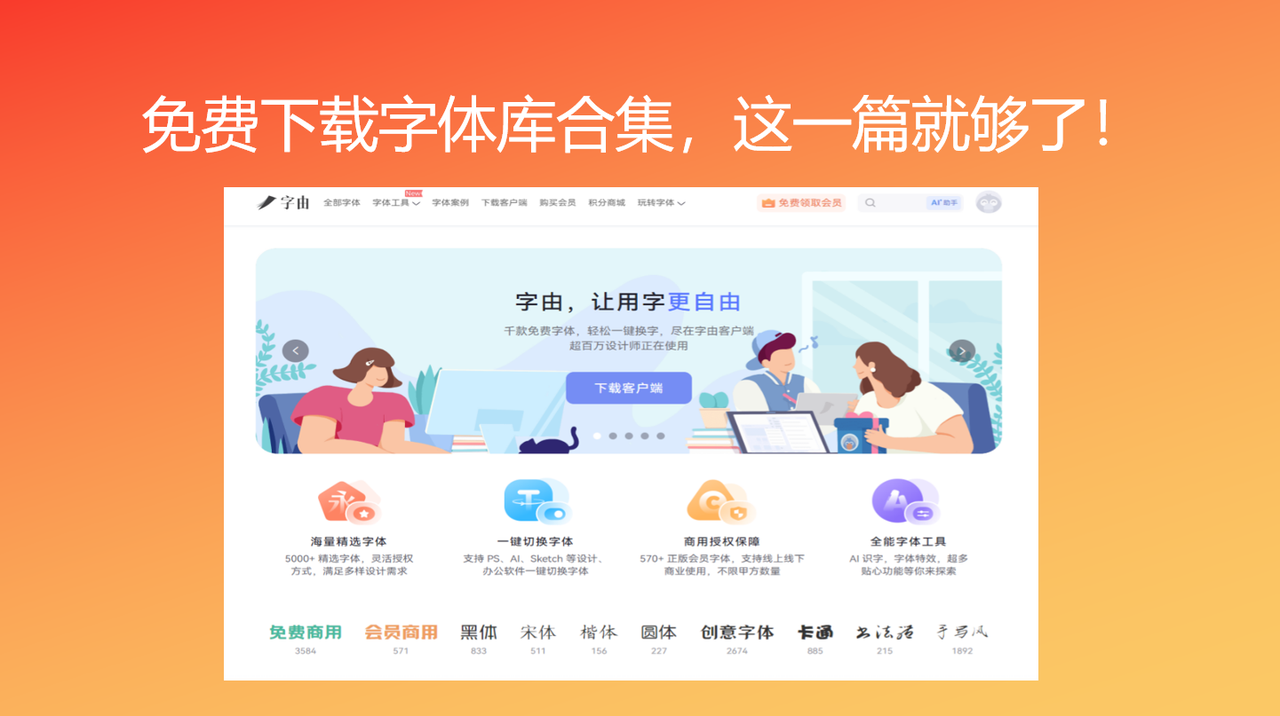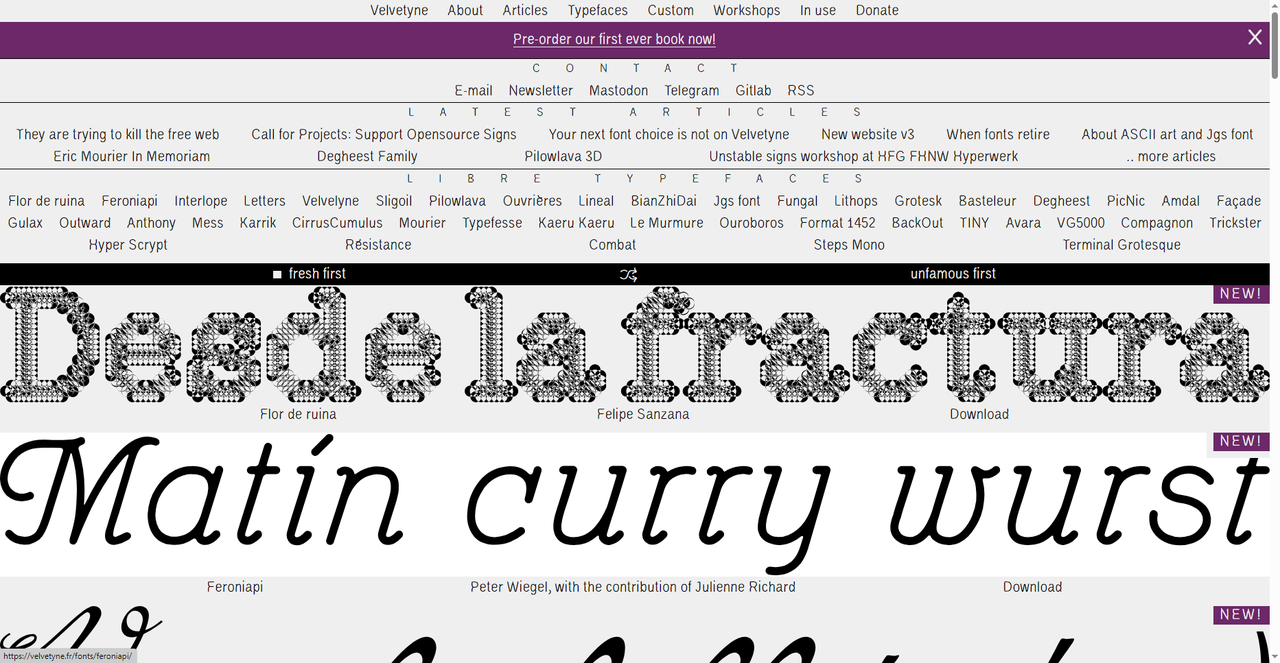
免费下载字体库合集,这一篇就够了!
相信各位和及时的浏览器收藏夹里肯定有专门分类收藏字体网站的收藏栏,看到别人推荐就点进去收藏,时间一长肯定有不少积累了。但是真正做项目的时候反而开始头疼要从这些花里胡哨的网站挑选哪个,有的网站已经好久都没有更新了,有的是分类太乱翻不到想要的,有的还要下载客户端,或者是注册邮箱,最后往往还是去搜“免费下载字体库”,从头开始找。今天我就为各位设计师推荐 5 个真正好用、经常能拿来使用的字体库,想要免费下载字体库,看这一篇就够了!
我经常用的免费下载字体库是字由。它里面涵盖了 5000 款字体,直接打包成一个超级字体库,它不需要你一个一个下载、安装客户端等等麻烦的步骤,你只需要点进网页版然后通过手机号注册即可。下面我会分享详细的使用教程。
- 按类型:黑体、宋体、书法体、手写体、Sans Serif、Serif 等
- 按热度:每款字体右下角有使用次数,优先选热度高的,比如“优设好身体”使用量达499万次
我可以推荐几款我自己经常用到的字体:
- 优设好身体(499万次使用):优设团队出品,字形方正饱满,适合正文排版和简洁标题。做画册、公众号配文很好用。
- 字由源黑95(6.5万+次使用):一款厚实稳重的黑体,字重足够“黑”,适合做标题、海报主视觉,视觉冲击力强。
- 点字婴宝(12万次使用):可爱风格的手写字体,圆润稚趣,适合母婴、儿童、萌系风格的设计。
- 字由玉润体(6.7万+次使用):圆润柔和的字体,笔画温润如玉,适合女性向、美妆、护肤等柔和风格的设计。
2、Velvetyne
Velvetyne 是一个来自法国的开源字体合作社,把自己定位为“自由字体合作社”。它的免费下载字体库里全是开源字体,可以免费商用,甚至允许修改和再分发。这样自由度如此之高的免费下载字体库合集网站基本上可以满足你的一站式需求,尤其是那些需要自主设计字体的字体设计师们。从图中不难看出首页有丰富的字体类型,Flor de ruina、Feroniapi、Interlope、Gulag、Outward、Anthony、Mess、Karrik、Letters……风格非常多元,每一款都有设计师的详细信息,可以点进去查看详情。
3、Collletttivo
这个网站是一个开源字体代工厂,也是设计师们协作创办的网络,这个网站主打宣传“通过相互交流和协作促进字体设计实践”,目前这个网站有16款开源字体,展示了7款:Borges、Ronzino、Aujournuit、Abasans、Coconut、Apple Grotesk、Sinistre。这款免费下载字体库合集中的字体适合追求简洁、现代感的设计师,尤其是品牌设计、网页设计项目。下载方式也很直接。
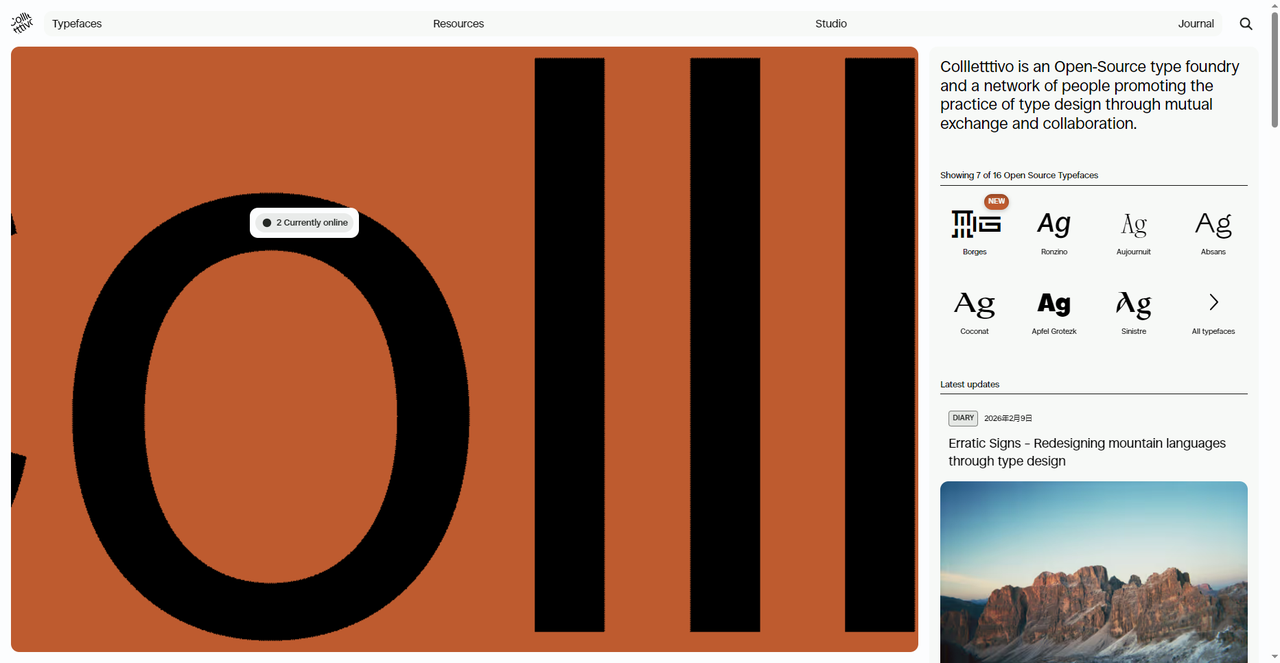
4、Pixel Surplus
这个免费下载字体库的特点是既有付费的字体包(通常打包出售很划算),也有不少免费字体可以单独下载。截图中的两款免费字体质量都不错:New York 是一款经典的衬线体,适合杂志排版;Futura 1986 则是基于 Futura 的做旧版本,适合复古风格设计。如果你想要一次性获得大量字体,可以考虑付费包,如果只想找几款免费应急,直接搜索“free fonts”就能找到很多。同时也别忘了版权相关信息提前查看一下。
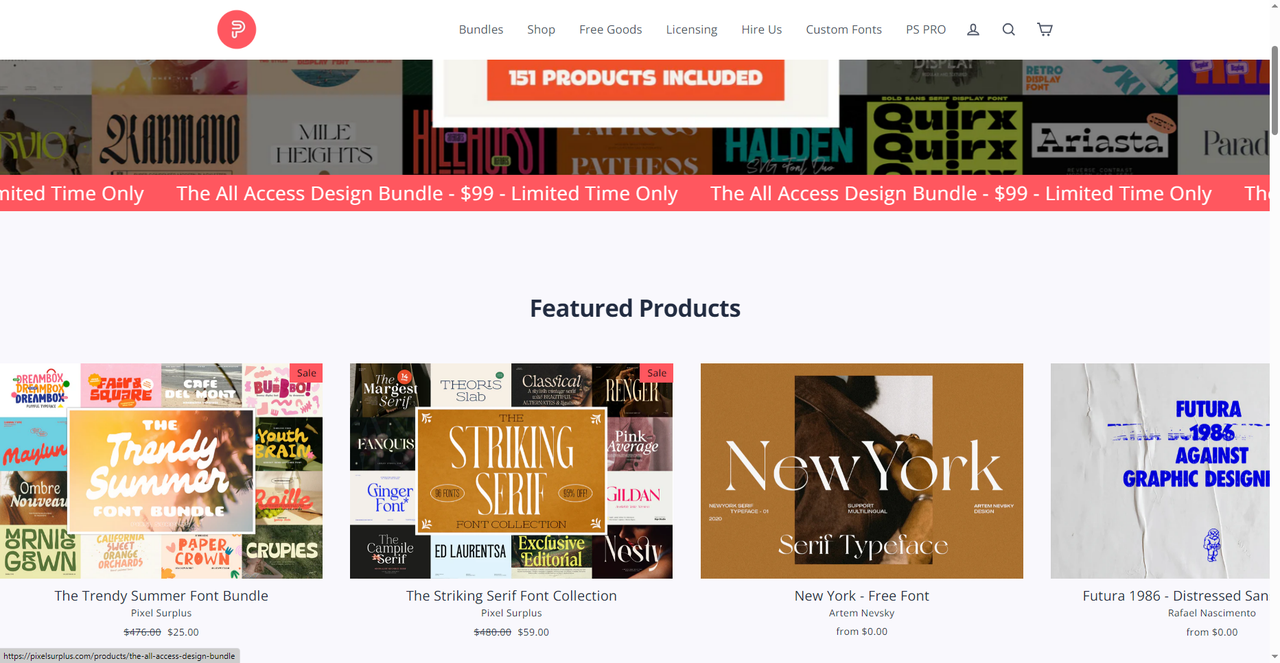
5、The League of Moveable Type
这个网站有点年头了,因为它是原创的、第一个的开源字体代工厂,从图中下半部分你可以看到一长串知名品牌标志:WIRED、.NET MAGAZINE、Discovery、世界卫生组织、SUBWAY、DC COMICS、Barbie、华纳兄弟、Instagram、美国航空、7-11、饥饿游戏、ZDNet、玛莎百货、MasterClass、Whole Foods、TRESemmé、Adele、Jack Ryan……这些都是使用过他们字体的客户。这个网站就是著名的 The League of Moveable Type(可移动字体联盟),成立于2009年,是最早的开源字体代工厂之一,非常的权威,如果你想要经典字体,可以来这里找找。